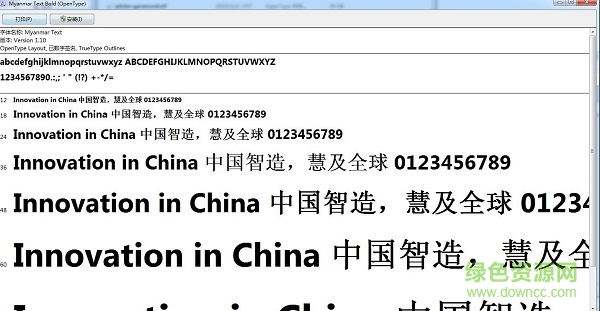
myanmar text字體是一款支持拉丁文字、緬甸文輸入的無襯線字體,該字體結(jié)構(gòu)嚴謹,字型飽滿雄峻,清晰易讀,可以用作廣告字體的標題或宣傳標語,歡迎大家免費下載!
1.拉丁文字是世界上應(yīng)用最為廣泛的文字,腓尼基人在公元前1600年發(fā)明了以符號代表發(fā)音,不僅是代表意思和物體的23個字母,公元一世紀古羅馬采用并修改了希臘字母最終完善成具有23個字母的拉丁字母體系。
2.1000年后加了U、W,1500年后加了J。6世紀的安塞爾字體和小安塞爾字體是小寫字母的形成的過渡字體。公元8世紀產(chǎn)生了卡羅琳小寫字體。
3.15世紀羅馬大寫字體和卡羅琳小寫字體通過意大利等國家的修改設(shè)計完美融合在一起。
4.阿拉伯數(shù)字是11世紀由印度傳到歐洲的;15世紀隨著印刷業(yè)的發(fā)展,標點符號成為專業(yè)書寫符號。